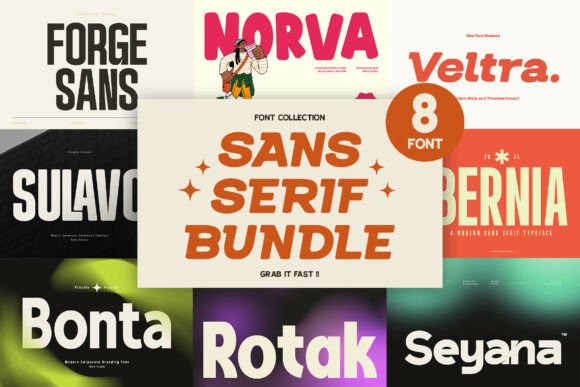
Sans Serif Bundle Collection
หากคุณกำลังมองหาเนื้อหาคุณภาพสูงเช่น Sans Serif Bundle Collection แพ็คเกจพรีเมียมนี้เป็นตัวเลือกที่ยอดเยี่ยมสำหรับโปรเจ็กต์สร้างสรรค์ของคุณ
สร้างขึ้นอย่างแม่นยำ Sans Serif Bundle Collection ให้เวกเตอร์ที่สะอาด พิมพ์ตัวอักษรที่ราบรื่น และใบอนุญาตเชิงพาณิชย์เพื่อความสบายใจ